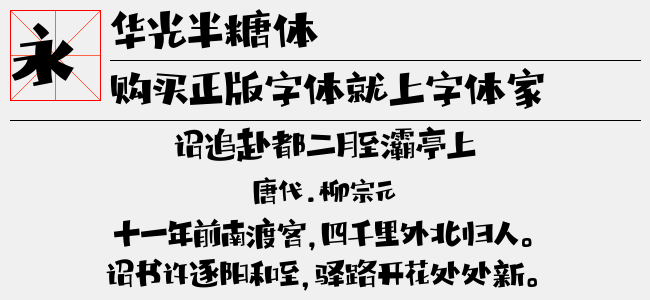
华光半糖体(2.98 MTTF中文字体下载)
华光半糖体 字体大小2.98 M,包含了6763个汉字以及附加其他英文字体和阿拉伯数字,属于青鸟华光字库。华光半糖体(TTF)可以免费下载,商业用途请自行购买版权,它的特征就是个性,海报,广告,卡通,采用安装嵌入的安装方式,支持符号拉丁文日文中文等语言
字体名称:华光半糖体